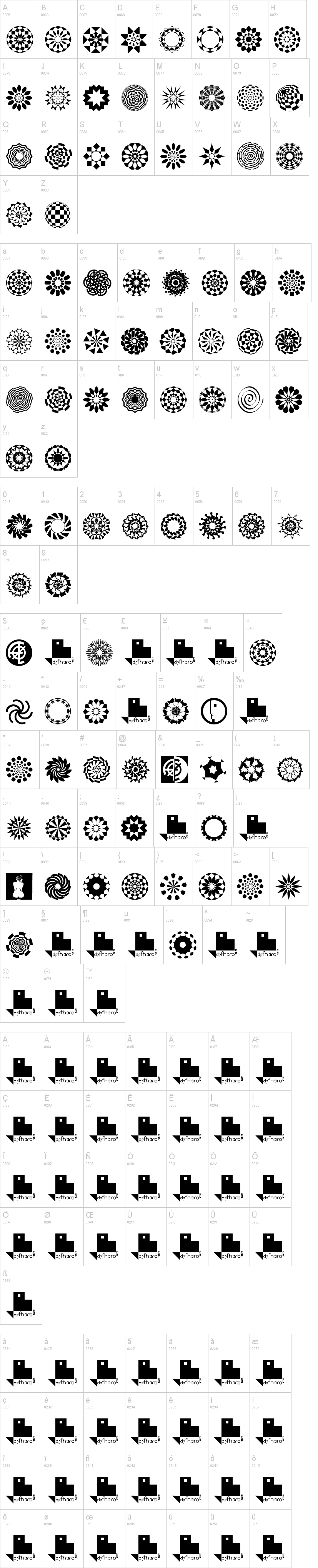
Note of the author95 Clip art in a font!
Esta colección de Clip art ha nacido de formas geométricas básicas y complejas moviéndose y girando sobre el círculo, inspirada también en los diseños de la colección de relojes de diseño y más concrétamente a la serie Op-art creada por mí al final de los 80.